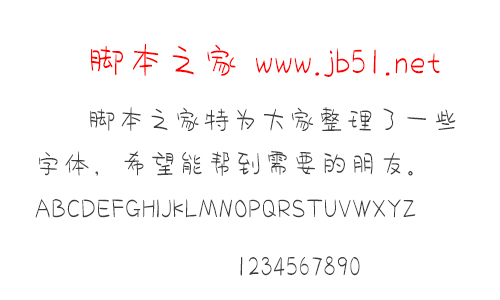
人間不正經(jīng)指南是一款非常有意思的個性手寫藝術(shù)字體,風(fēng)格比一般的字體更有特色,連貫字跡顯得干練而不凌亂,清新簡明,具有很好的視覺感,適合應(yīng)用于藝術(shù)設(shè)計、平面宣傳設(shè)計、網(wǎng)頁設(shè)計,書法字帖等領(lǐng)域,歡迎喜歡人間不正經(jīng)指南字體的朋友前來下載使用。